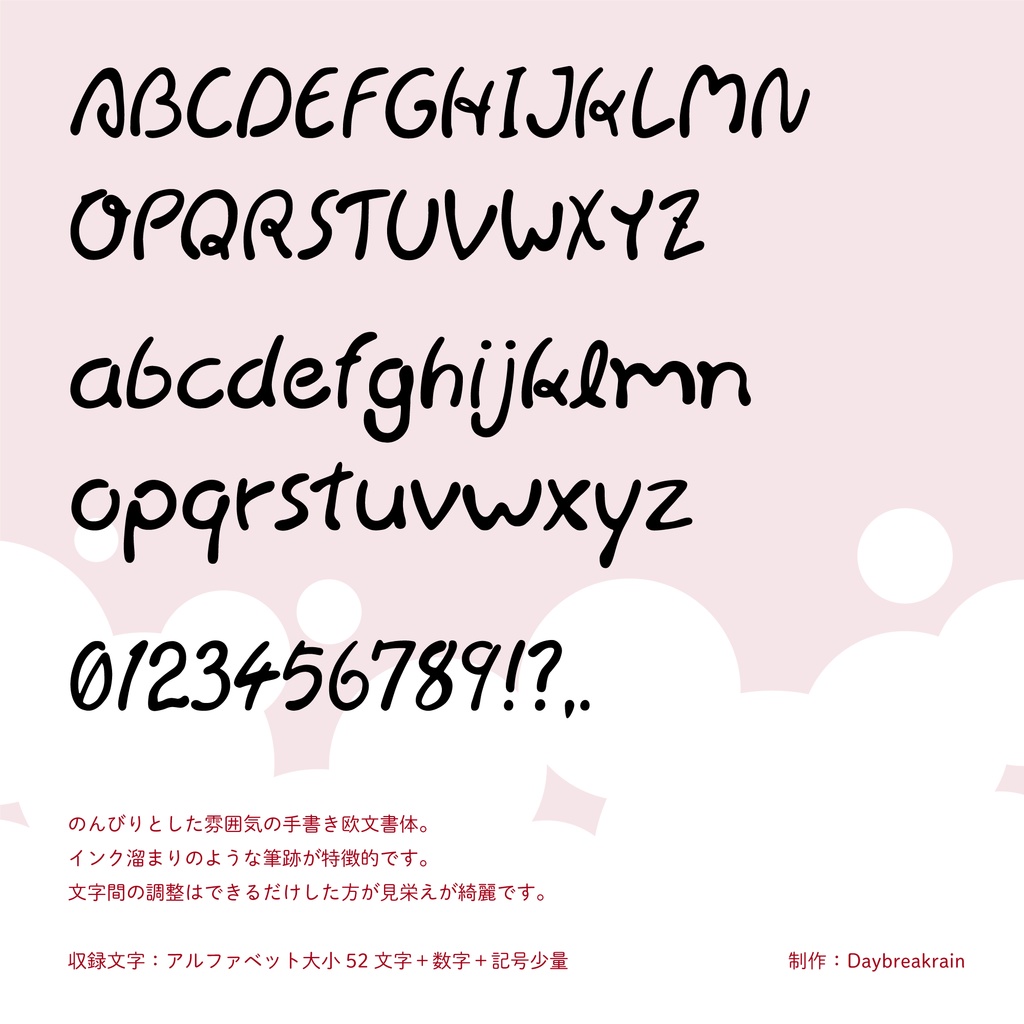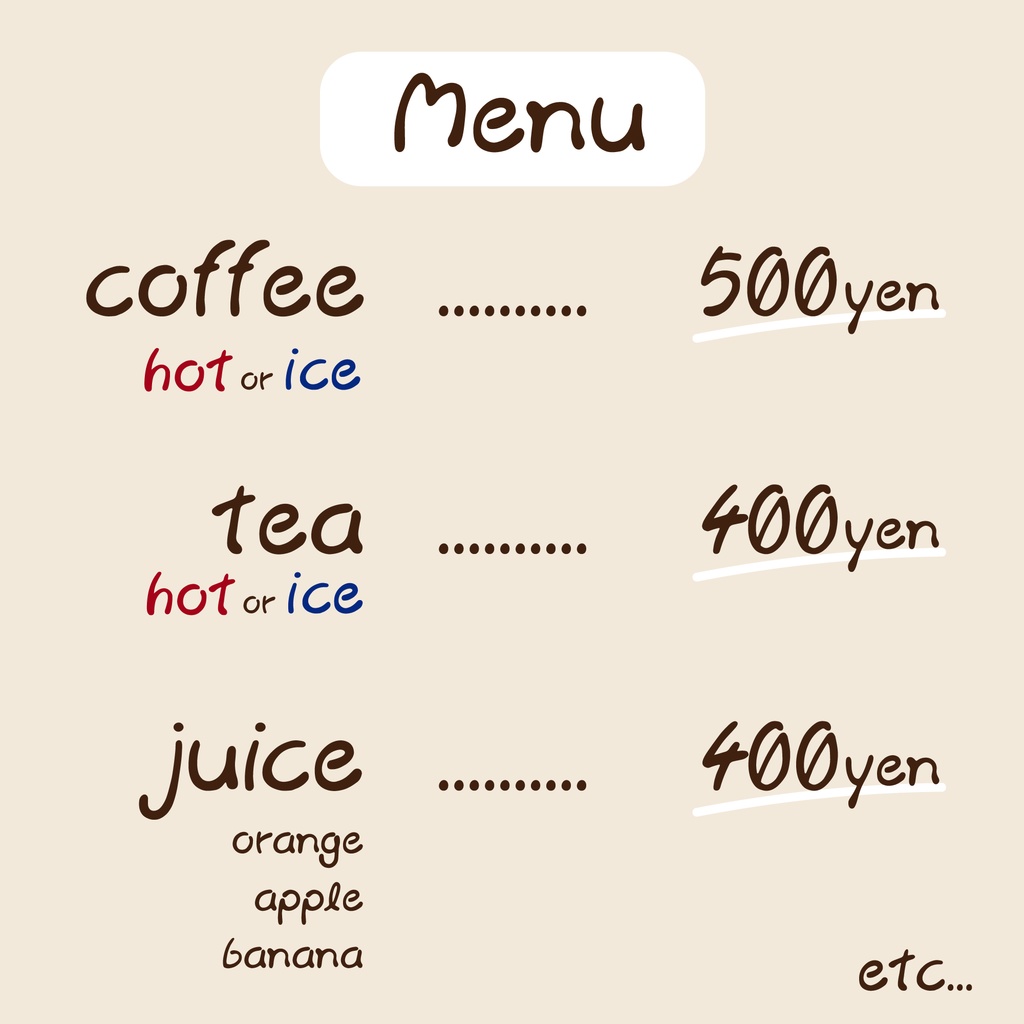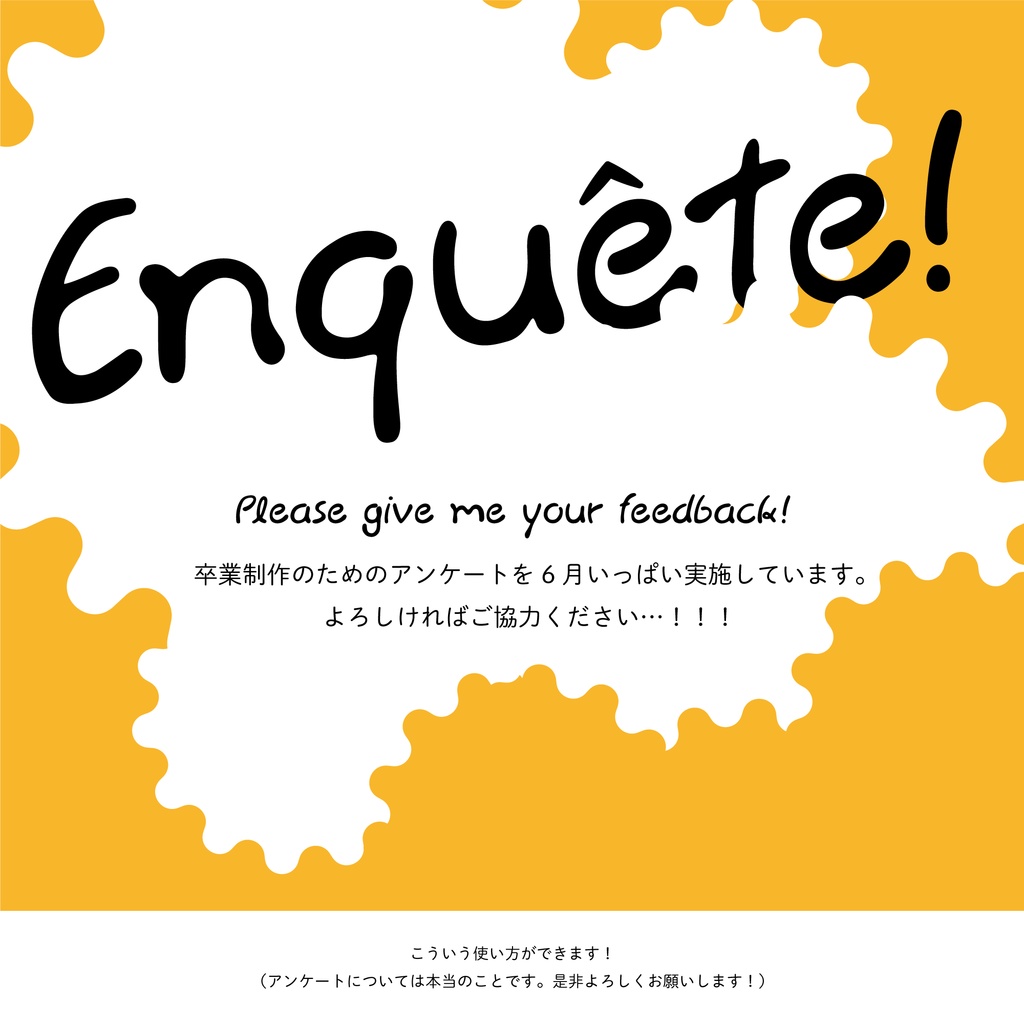
Akubi Font
Akubi Font のんびりとした雰囲気の手書き欧文フォントです。 題字や見出しなどにご利用ください。 必ずreadmeと書かれたテキストファイルをお読みになってからご利用ください。 【収録文字】 ・アルファベット大小52文字 ・数字 ・記号少量 ファイル名は「Akubi_Font」となっています。 データはOTFデータです。 【免責事項】 ・商業、個人問わずご利用できます。 ・再配布、商標登録、複製、改変不可 ・利用の際の報告は任意です 。 Akubi Fontの著作権は全てdaybreakrain/まえださゆきに帰属します。 自作発言等はお控え下さい。 また、利用者様が当フォントを利用した際に負った問題、損害について作者は一切の責任を負いません。 フォントをダウンロードした時点で利用規約に同意したものと見なします。 ご利用は自己責任でお願い致します。 通常版と投げ銭版のデータは同じものです。 フリーフォントとして配布しますが、もしよろしければ投げ銭版からお好みでBoostしてご支援いただけますと嬉しいです。 励みにさせていただきます。 更新履歴 2021.6.10 Akubi Font Ver.1.00配布 6月いっぱいまで、卒業制作のためのアンケートを実施しています。 よろしければご協力いただけますと幸いです。 どうぞ宜しくお願いいたします…!! https://forms.gle/5dSLCgeWaKJh67tUA